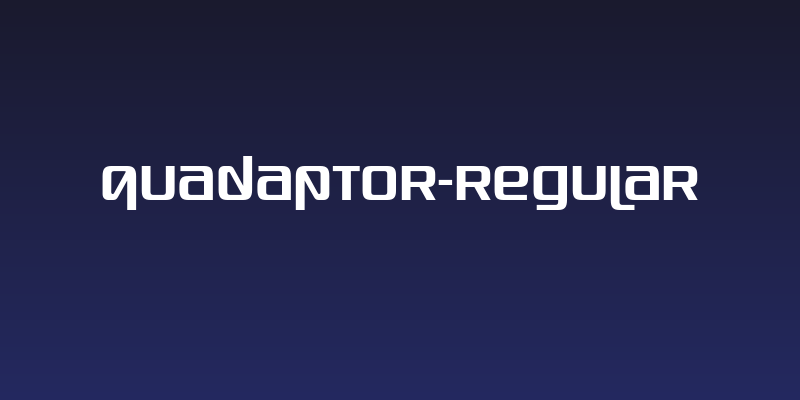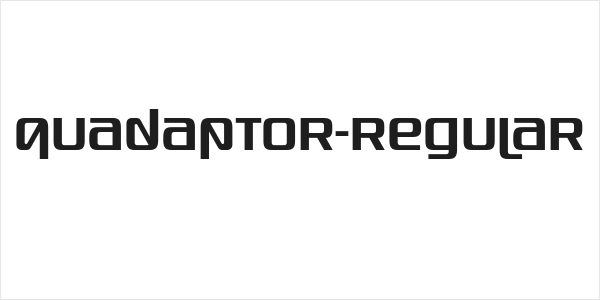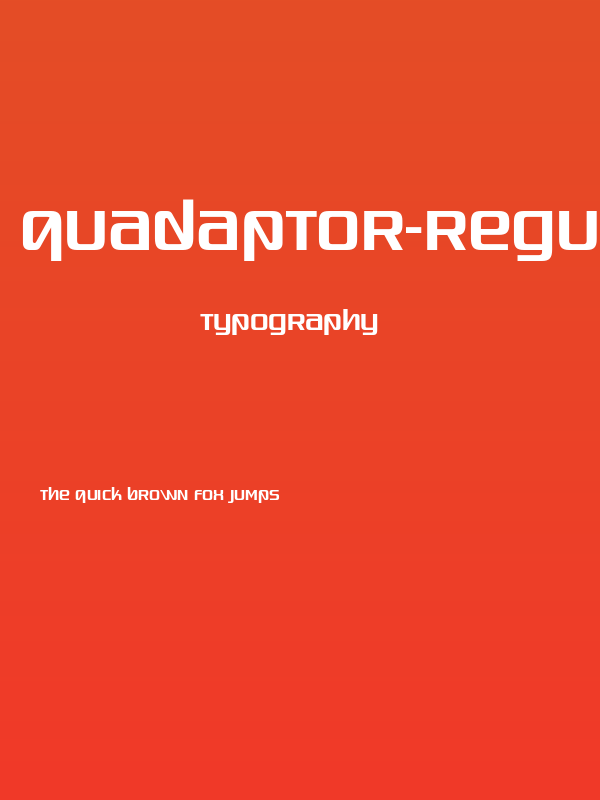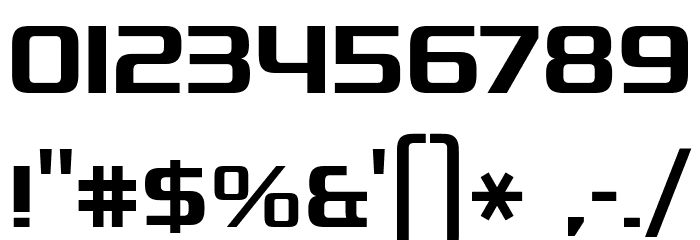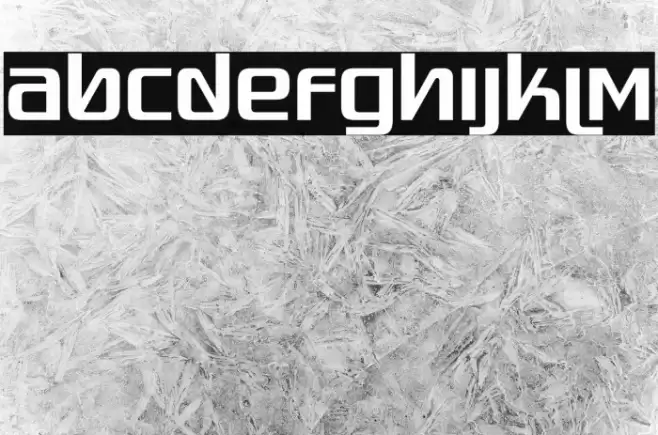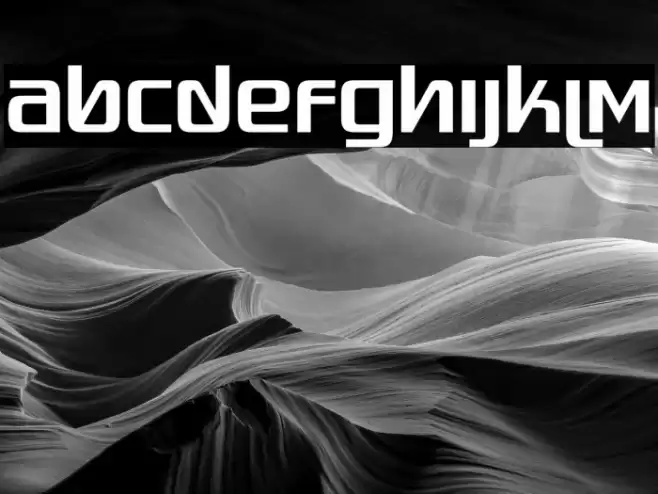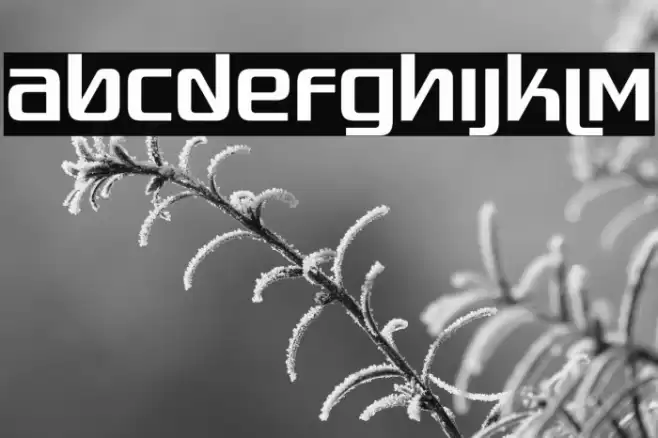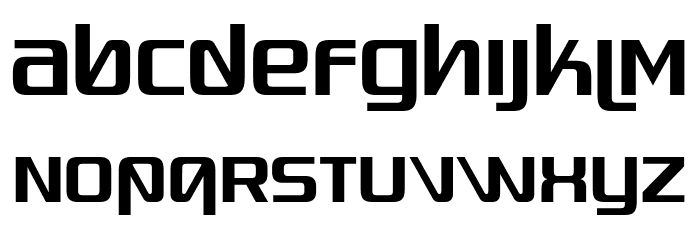
Quadaptor-Regular Font
| Caso de uso | Headlines, Logos, Digital Interfaces |
| Projetos propostos | Ideal for technology branding, sci-fi themed projects, digital interfaces, and modern advertising. |